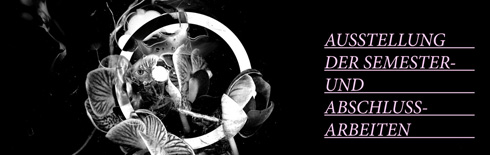
Gut ein Viertel der Kommunikationsdesigner lebt von weniger als 15.000 € Nettoeinkünften pro Jahr. Das ist die ernüchternde Bilanz einer Online-Umfrage, die der BDG Berufsverband der Deutschen Kommunikationsdesigner e. V. unter angestellten und freiberuflichen Kommunikationsdesignern vom 13. 1. bis zum 19. 1. 2010 durchgeführt hat. 15.000 € pro Jahr, das sind 1.250 € monatlich für eine Berufsgruppe, die eigentlich gesellschaftliches Ansehen genießt.
Ein seltsames Ungleichgewicht ist zu beobachten: Design ist innerhalb der Kulturwirtschaft ein gewichtiger Faktor geworden. Im Jahr 2006 verzeichnete der Bereich Kommunikationsdesign einen Umsatz in Höhe von 12,6 Mrd. €.* Das sind Summen die unendlich weit von der Lebenswirklichkeit der meisten Designer entfernt sind. Lediglich ein Drittel der 1.016 Teilnehmer der Umfrage gab an, mehr als 25.000 € jährlich zu verdienen.
Im Jahr 2006 bewegten sich 120.000 Designer auf dem Markt, darunter waren in etwa 92.000 Kommunikationsdesigner.* Rechnet man die Zahlen der Umfrage des BDG hoch, so ist davon auszugehen, dass in etwa 23.000 Kommunikationsdesigner jährlich weniger als 15.000 € netto verdienen. Das sind zum großen Teil Designerinnen und Designer mit einem Hochschulabschluss, die laut unseren Ergebnissen durchschnittlich 43 Stunden die Woche arbeiten. 7 Prozent der Teilnehmer (das wären hochgerechnet 6.440 Designerinnen und Designer) gaben gar an, dass sie Nettoeinkünfte zwischen 0 und 5.000 € jährlich erzielen. Das ist nicht nur ernüchternd, das ist bitter.
Die Umfrage des BDG ist eine Reaktion auf eine Gehaltstabelle, die im »Stern« vom 7. Januar 2010 veröffentlicht wurde. Danach verdienten Grafiker und Designer monatlich 4.690 € brutto im Jahr 2008. Seit 1990 haben sie damit eine Gehaltssteigerung um 85 Prozent erzielt. In einer kleinen Anmerkung wird darauf hingewiesen, dass in diesem Fall die Anzahl der Befragten weniger als 25 betrug. Es wird Zeit, ein realistisches Bild vom Traumberuf Kommunikationsdesigner zu malen.
* Die Zahlen entstammen einem Forschungsgutachten, das der Kulturwirtschaftsforscher Michael Söndermann im Auftrag des Bundesministeriums für Wirtschaft und Technologie erstellt hat.
Diese Schriftfamilie braucht nicht viele Worte, deshalb fasse ich mich kurz und stecke meine ganze Energie in das Schriftmuster. Vorlage für Barbieri war eine handgezeichnetes Plakat für eine deutsche Aufführung der Oper »Der Barbier von Bagdad« in den 60er Jahren. Andrés Torresi und Marta Sánchez digitalisierten die Schriftzeichen für die Amsterdamer Foundry ReType und bauten sie zu einer sechsköpfigen Familie aus, mit den Strichstärken Light, Regular, Book, Bold, Black und Heavy.
Mich hat Barbieri sofort an die Typografie einer alten BRAVO erinnert, freilich mit etwas mehr Raffinesse in den Buchstabenformen als damals, wo doch eher existierende Standardschriften mit Photosatz-Effekten versehen wurden. Die Arbeit mit den 6 Barbierei-Schnitten macht ungeheuren Spaß, weil sie unmittelbar Erfolgserlebnisse bescheren. Gerade das Zusammenspiel der Strichstärken öffnet überraschende Gestaltungswege.
Die Europäische Kommission hat heute offiziell den Sieger des Wettbewerbs um das neue EU-Bio-Logo bekannt gegeben. In den letzten beiden Monaten haben etwa 130 000 Personen im Internet abgestimmt, um das neue Bio-Logo aus den drei Entwürfen der Endausscheidung auszuwählen (Fontblog berichtete). Das siegreiche Logo mit dem Euro-Blatt, für das 63 Prozent aller Teilnehmer gestimmt haben, hat Dusan Milenkovic entworfen, ein Student aus Düsseldorf. Der Sieger sowie der zweite und dritte Preisträger werden im Juli 2010 bei der offiziellen Preisverleihung durch die Generaldirektion Landwirtschaft und ländliche Entwicklung der EU-Kommission geehrt. Das Preisgeld beträgt 6000 EUR, 3500 EUR bzw. 2500 EUR.
Ab 1. Juli 2010 ist dieses EU-Bio-Logo für alle verpackten Bioprodukte, die in einem EU-Mitgliedstaat hergestellt wurden und die notwendigen Normen erfüllen, verbindlich vorgeschrieben. Für eingeführte Erzeugnisse ist es fakultativ. Neben dem EU-Logo können auch andere private, regionale oder nationale Logos abgebildet werden. In den nächsten Wochen wird die Verordnung über die ökologische Landwirtschaft überarbeitet, um das neue Logo in einen der Anhänge aufzunehmen.
Gerade lese ich beim Schockwellenreiter: »Haloscan schließt. Am 11. Februar 2010 schließt Haloscan seine Pforten. Damit werden alle Kommentare im Schockwellenreiter vom Februar 2005 bis April 2009 verschwunden sein.« Auch das Fontblog nutzte den kostenlosen JavaScript-Kommentarservice Haloscan, allerdings nur bis 2006. Ich muss mich also beeilen, mit meinem Rückblick, wenn wir noch ein paar Kommentare von damals lesen wollen.
Wer das Jahr 2006 systematisch durchforsten möchte, gehe auf diese Verteilerseite und klicke in der Navigation links auf den jeweiligen Monat, zum Beispiel Januar 2006, und lese dann von unten nach oben.
2006:
4. Januar 2006:Intel tritt mit einer neuen Hausschrift auf, einer modifizierten Neo Sans (interner Name: »Neo Sans Intel«). Das Vorbild wurde 2004 von Sebastian Lester entworfen. Der Mix aus Dax und DIN macht Schule, viele Marken und Unternehmen folgen in den darauf folgenden Monaten.
Bei der Ausgestaltung der Abschlussarbeiten geht es nicht nur um technisch-mediale Umsetzungen, sondern insbesondere um komplexe gesellschaftliche, soziale und kulturwissenschaftliche Themenstellungen. »Die kritische Auseinandersetzung mit aktuellen Zusammenhängen entspricht dem Ziel der Merz Akademie, die Studierenden zu eigenständigen Medienautoren auszubilden, die sich ihrer Verantwortung gegenüber der Gesellschaft bewusst sind.«